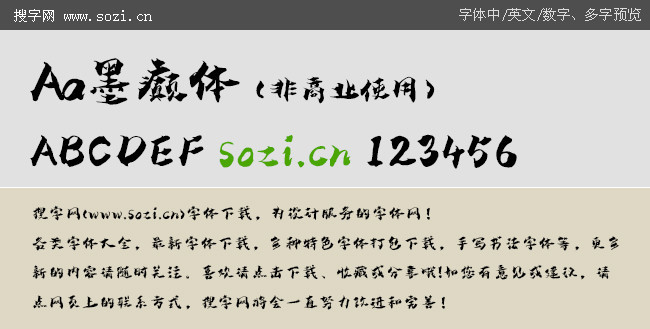
Aa墨癲體
搜字網(wǎng)給大家提供一款A(yù)a墨癲體(非商業(yè)使用)中文字體下載,該字體是一款非常漂亮的書(shū)法字體,工整簡(jiǎn)潔,具有強(qiáng)烈的視覺(jué)沖擊力,適用于平面宣傳設(shè)計(jì)、網(wǎng)頁(yè)設(shè)計(jì)、海報(bào)設(shè)計(jì)等應(yīng)用(此字體為個(gè)人非商用版,商用可以聯(lián)系QQ:1006760504)。